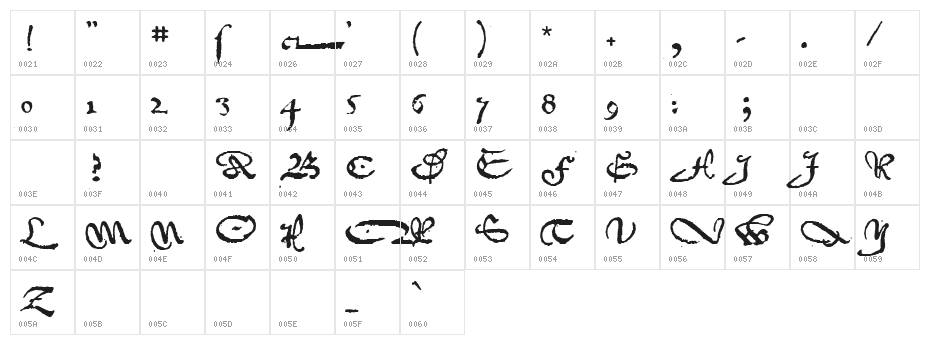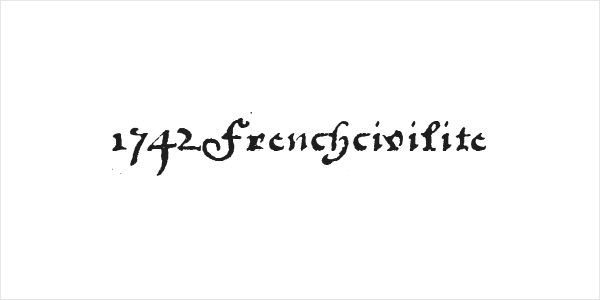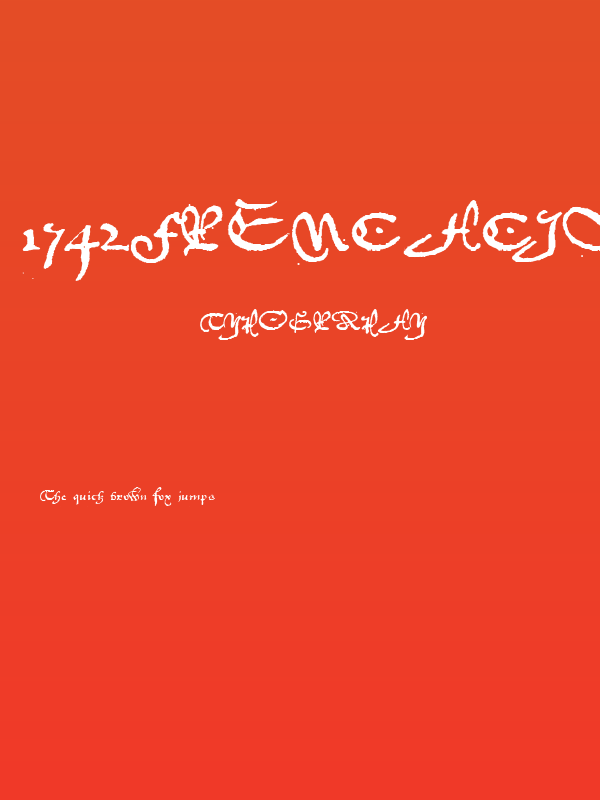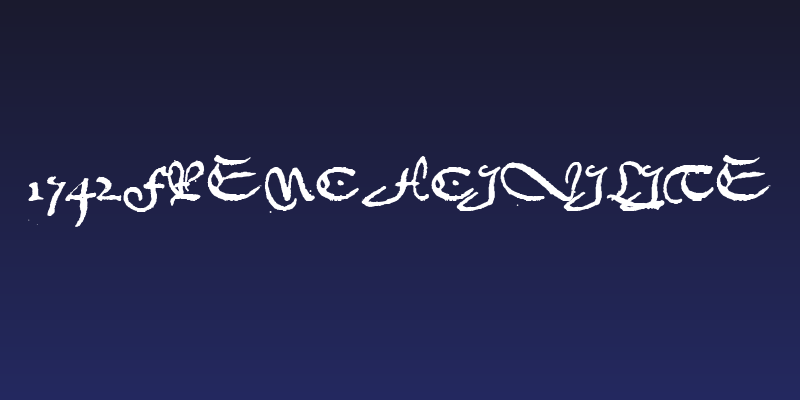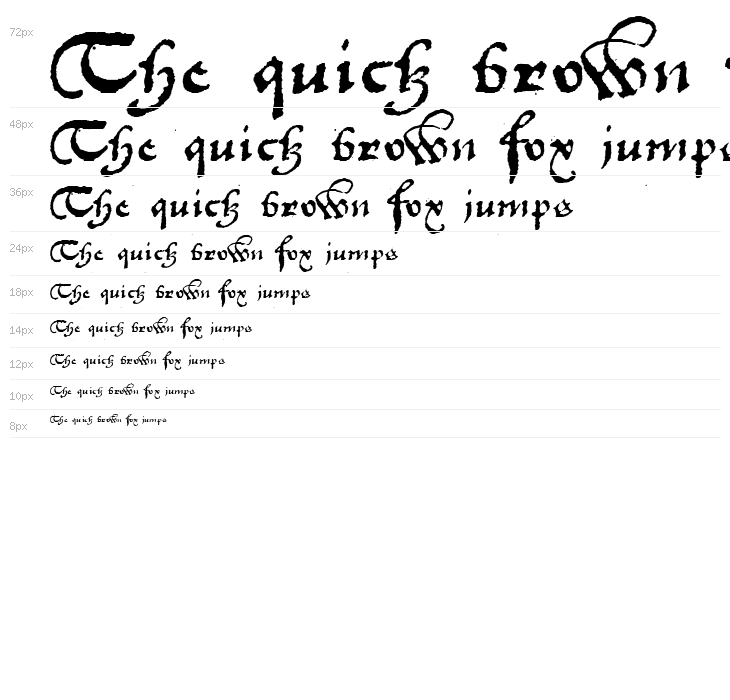
1742Frenchcivilite Font
| Caso d'uso | Decorative, Historical documents |
| Progetti proposti | Ideal for historical documents, invitations, certificates, and decorative projects that require a vintage aesthetic. |